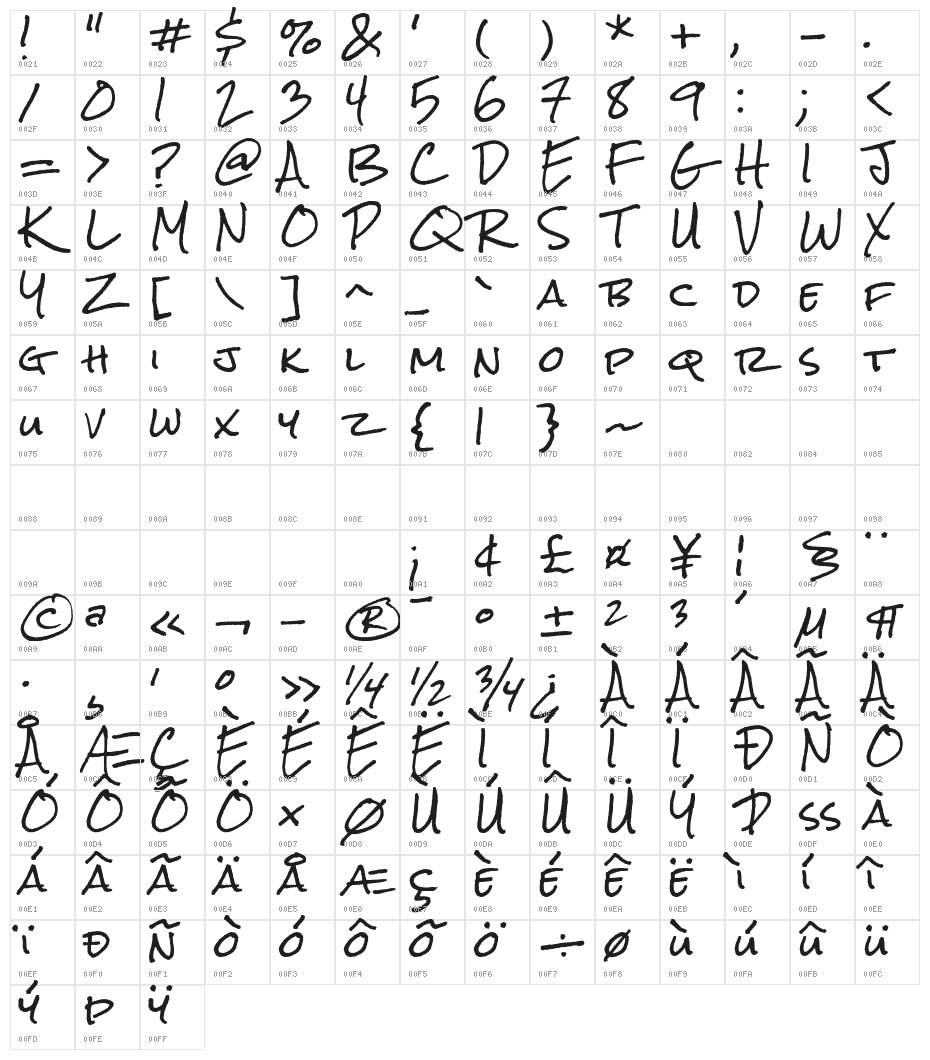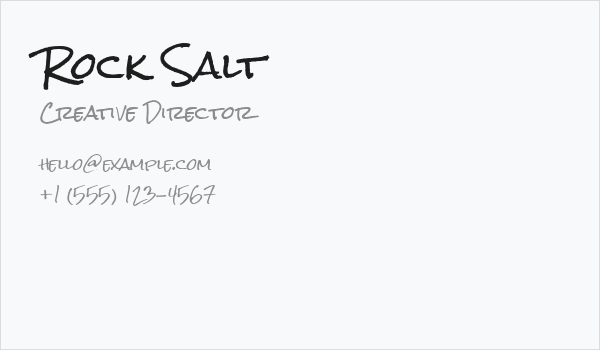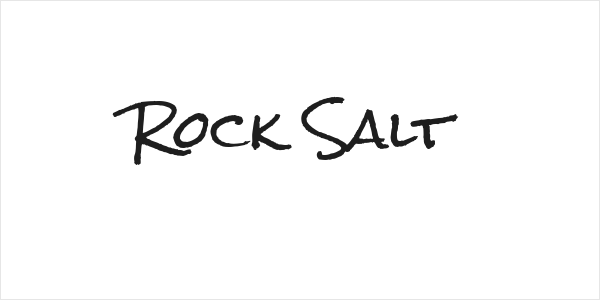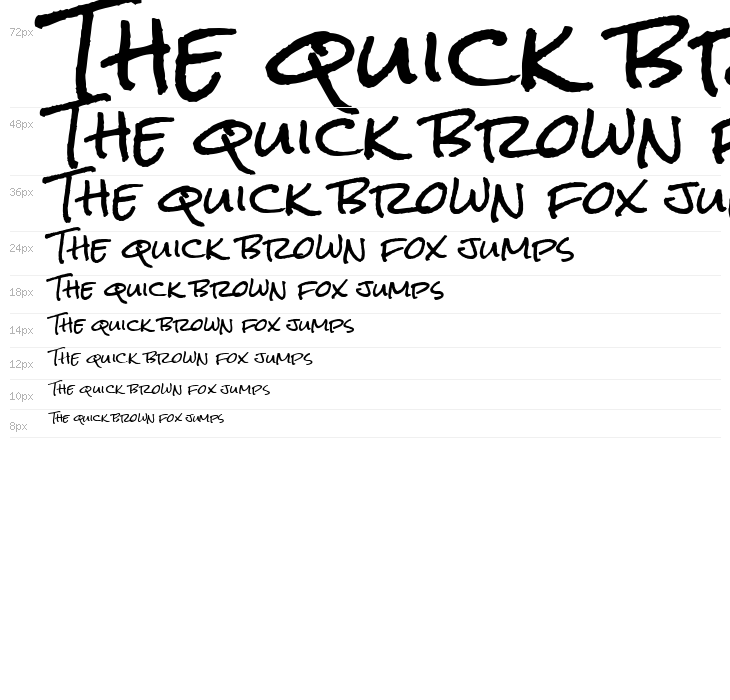
Rock Salt Font
| 全体的なスタイル | Casual, Organic |
| 用途 | Headlines, Creative projects, Personal branding |
| おすすめプロジェクト | Ideal for greeting cards, invitations, personal branding, and creative projects. |